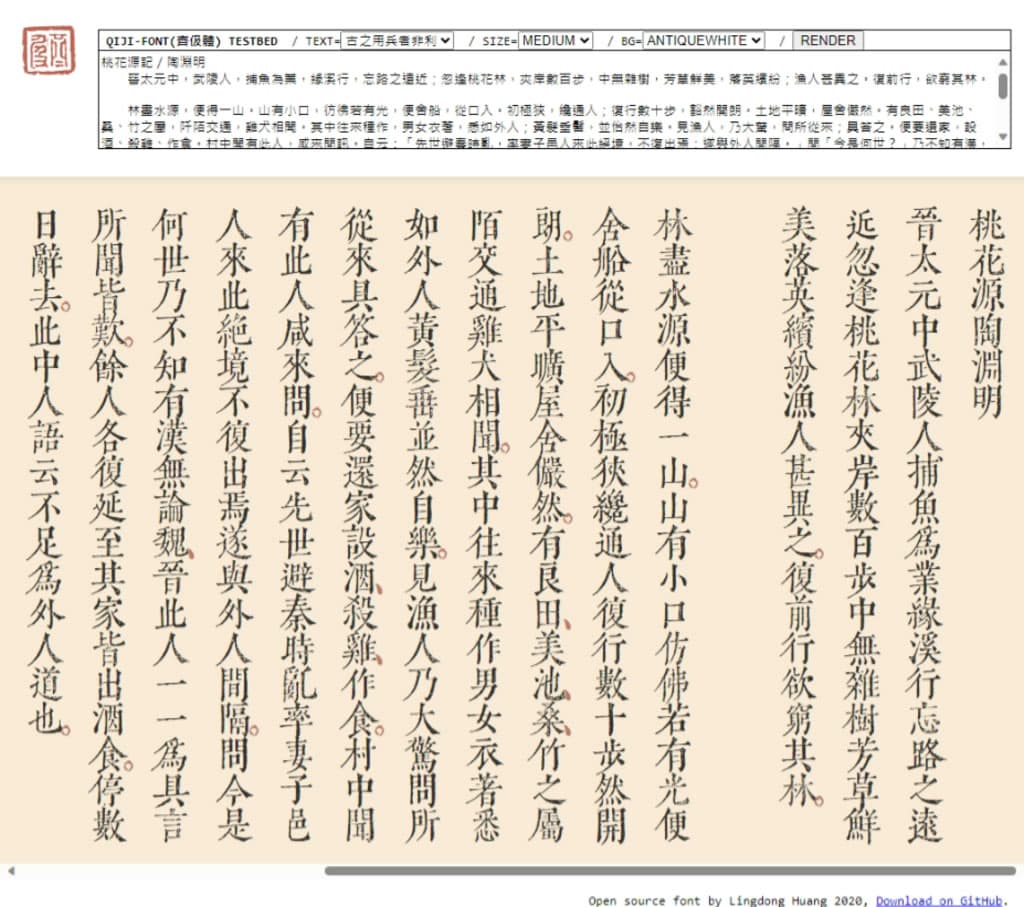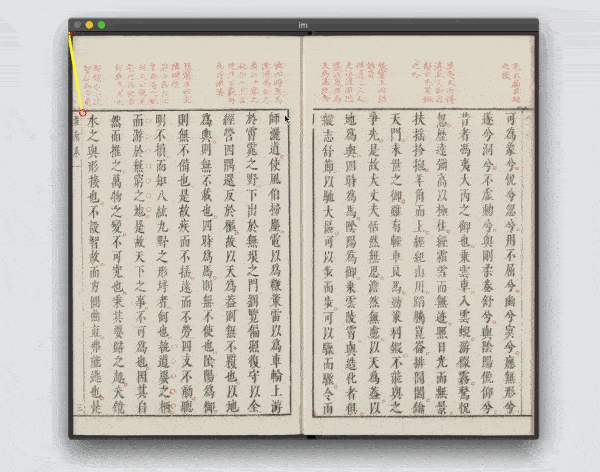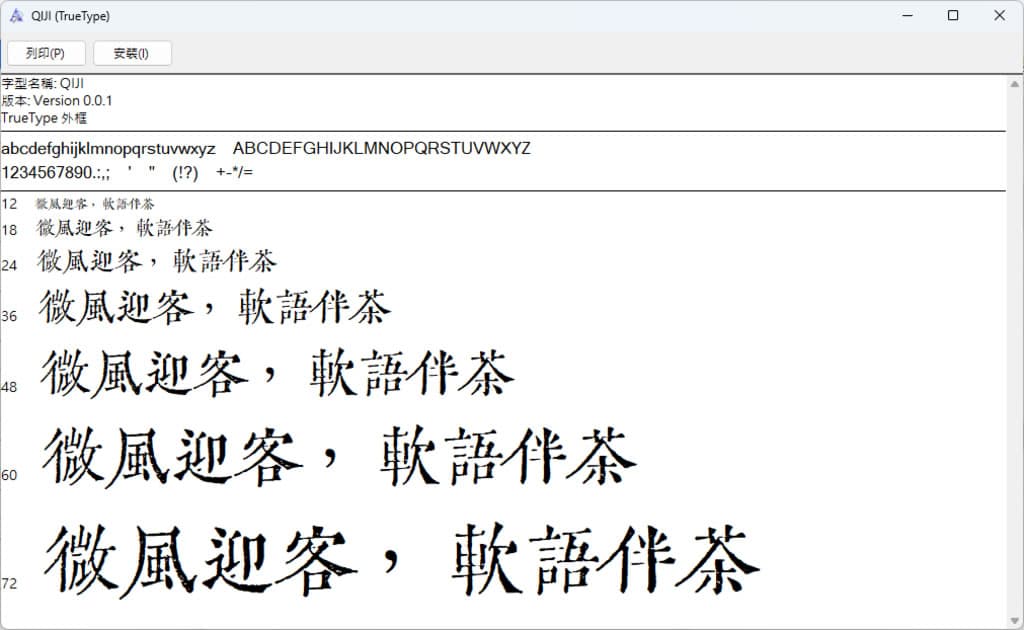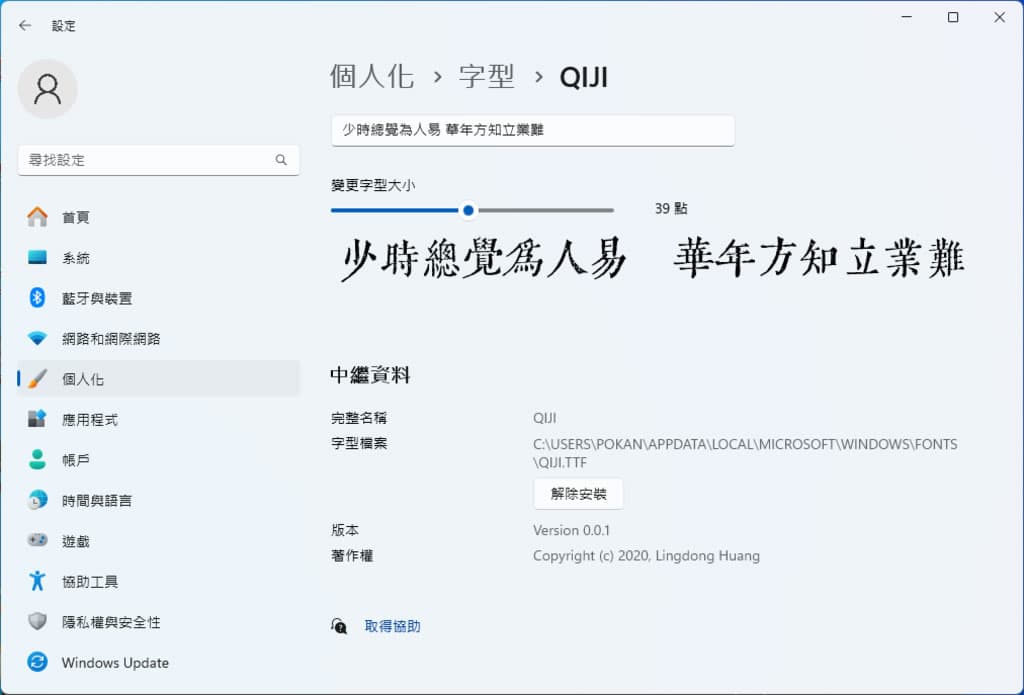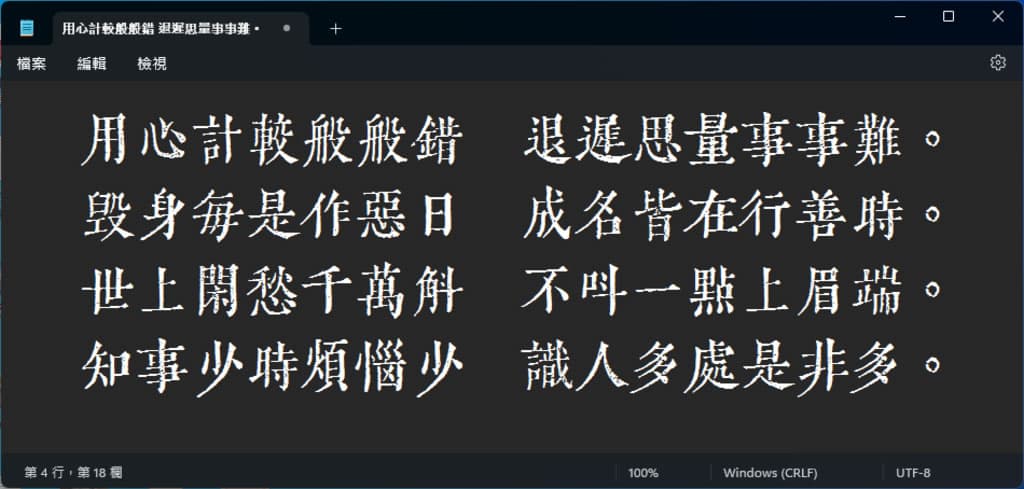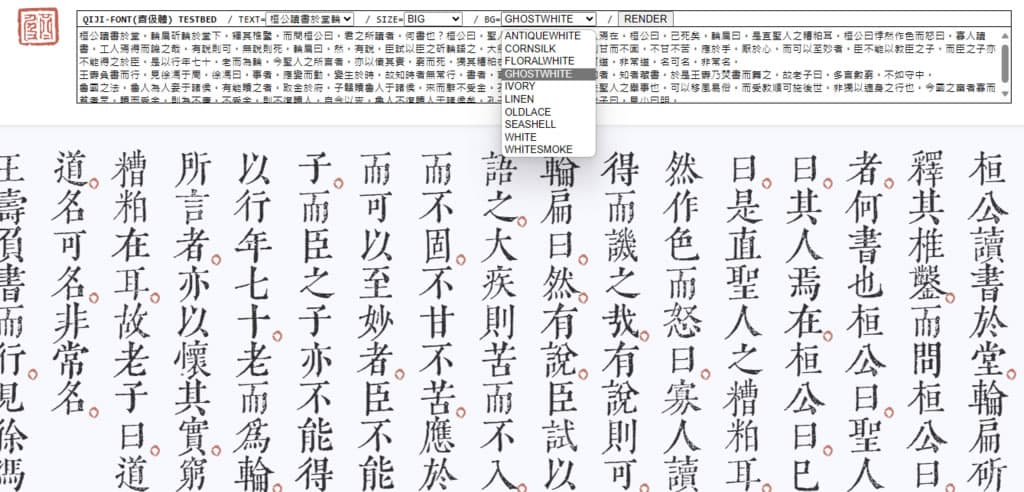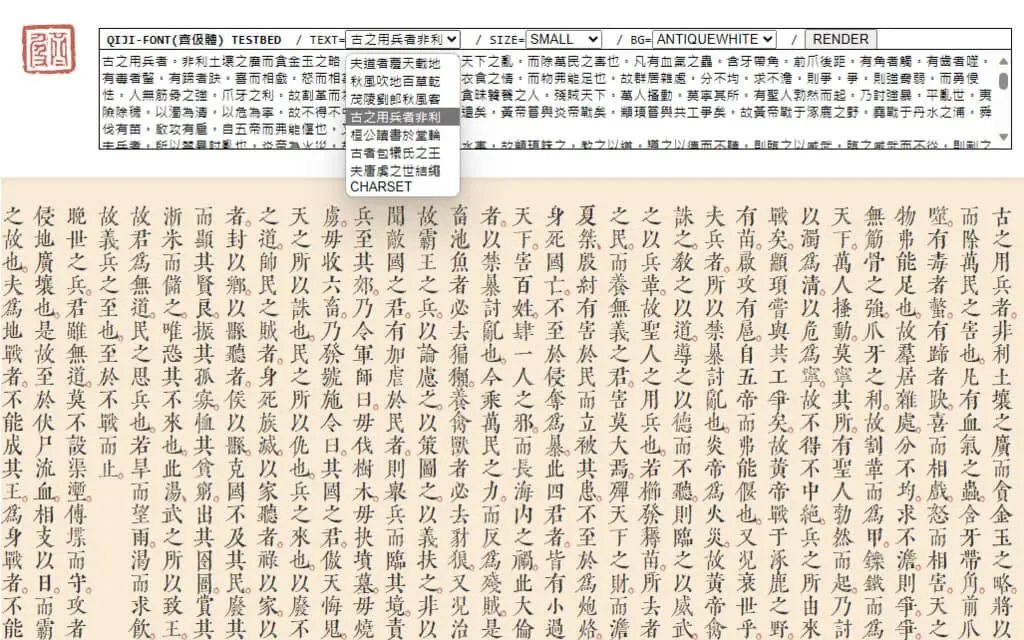
中文字體的橫、豎、撇、點、及折均有講究,還要考慮呈現時的美觀與清晰度,再加上中文字數也不少,因此,不論是手繪或用繪圖軟體來製作,要成就一套中文字型著實不易。而「令東齊伋體」的製作方式,則是將明代印刷刻本利用半自動電腦視覺和 OCR 的擷取方式,再透過人工篩選製作成一套開放原始碼的中文字型。
根據說明,「令東齊伋體」的字體取材自明代閔凌刻本內的《李長吉歌詩》和《淮南鴻烈解》兩本古籍,而字體的製作過程,首先是下載已將古籍掃描成高解析度的 PDF 檔案,並將其拆分為圖像。然後,在每個圖像的頂部手動放置一個網格,以產生字元的邊界框。接下來,為每個邊界框產生低多邊形蒙版,清潔圖像以去除紅色墨水列印的註釋。之後,對圖像進行閾值處理並輸入輪廓追蹤演算法,並使用度量來過濾不感興趣的形狀。這一步驟並不生成最終的字形,只是中間處理的一部分,準備圖像供後續處理,每個經過處理的縮圖進入神經網路中的中文 OCR 進行字元識別。然後,手動判斷 OCR 輸出,選擇最佳外觀實例並標記錯誤辨識的字元。最後,對於最終的字元集,自動生成每個字元的精細光柵渲染,以確保字元的視覺中心位於中心線上。使用閾值方法處理圖像,然後使用光柵到向量追蹤軟體將光柵渲染轉換為SVG。最終,使用 FontForge 的 Python 函式庫來生成字體檔案,完成字體生成過程。
最後,因作者名「令東」,而「齊伋」是來自首先使用套版印刷技術刻印書籍的明代刻書家「閔齊伋」,故中文取名為「令東齊伋體」,字體英文名為「qiji.ttf」,目前有 4569個獨特字形,涵蓋 5916個字元。如果想在線上直接看「令東齊伋體」的呈現效果,也可以進入 https://qiji-font.netlify.app/ 網站內自行文字來測試。
「令東齊伋體」的字體來源是復刻自明代木刻書籍內文字而成,非常適合出現於有傳統、古樸風格的場景中,可以試試。